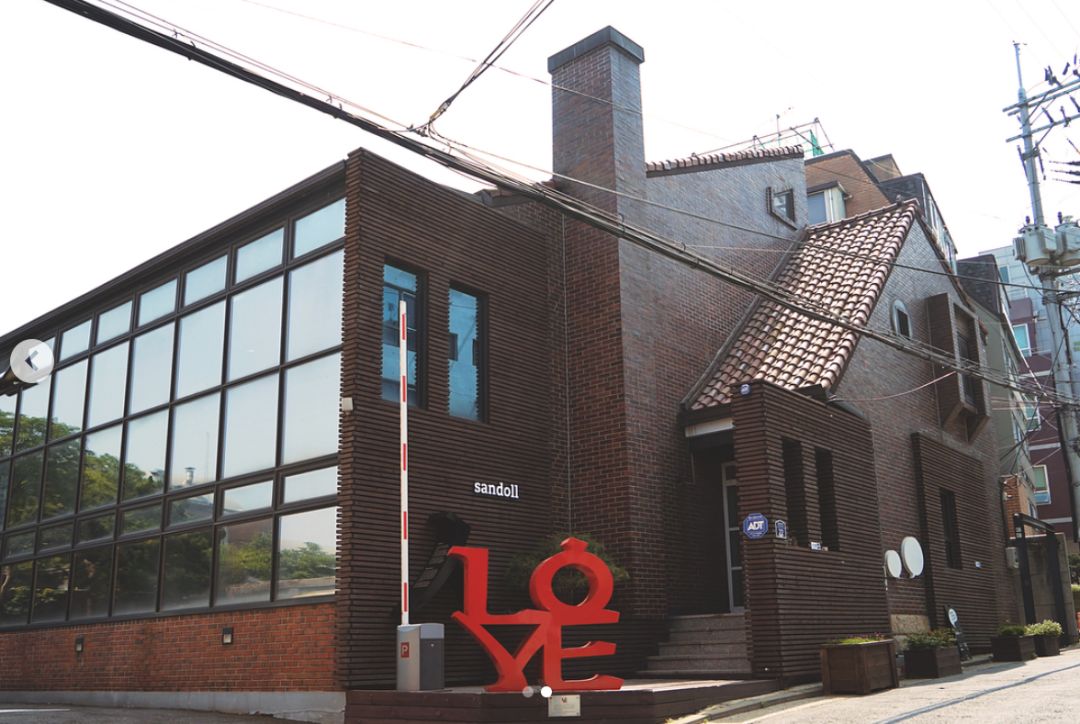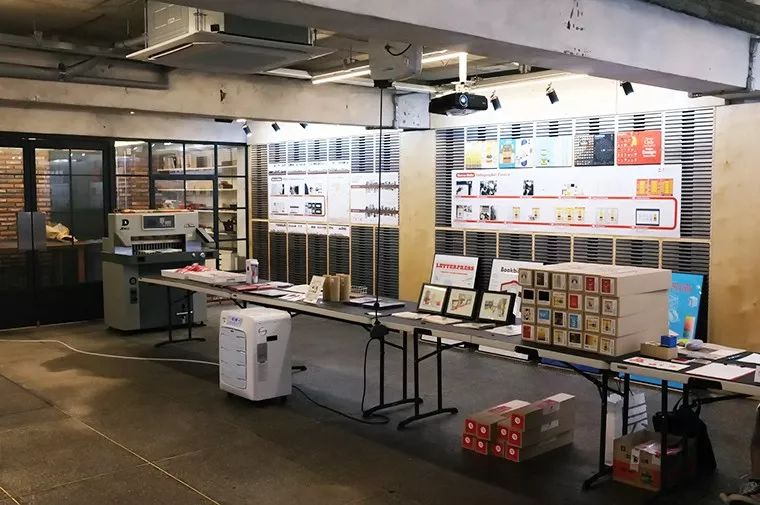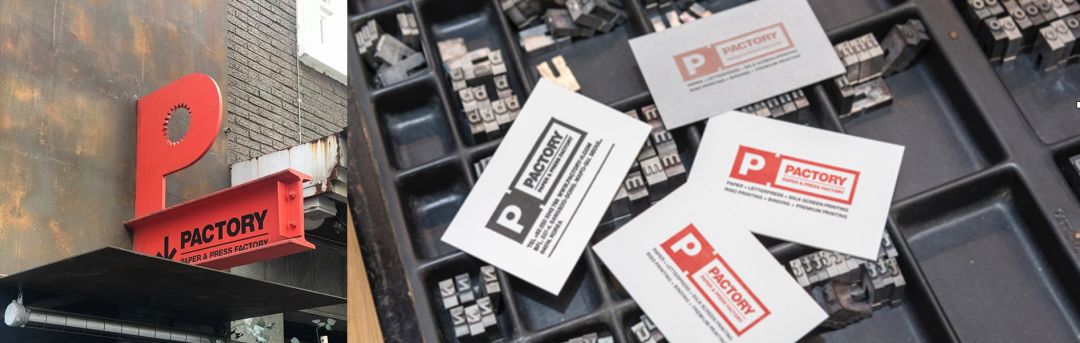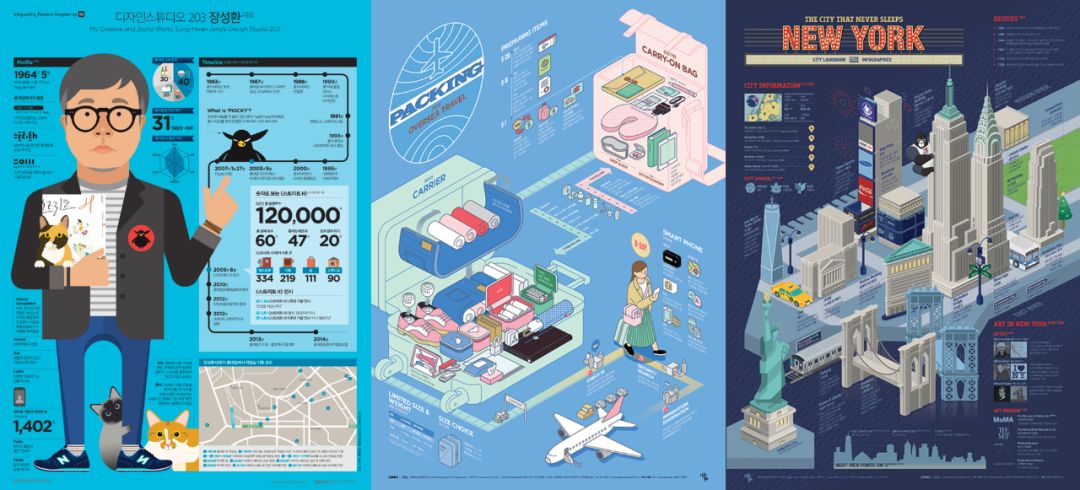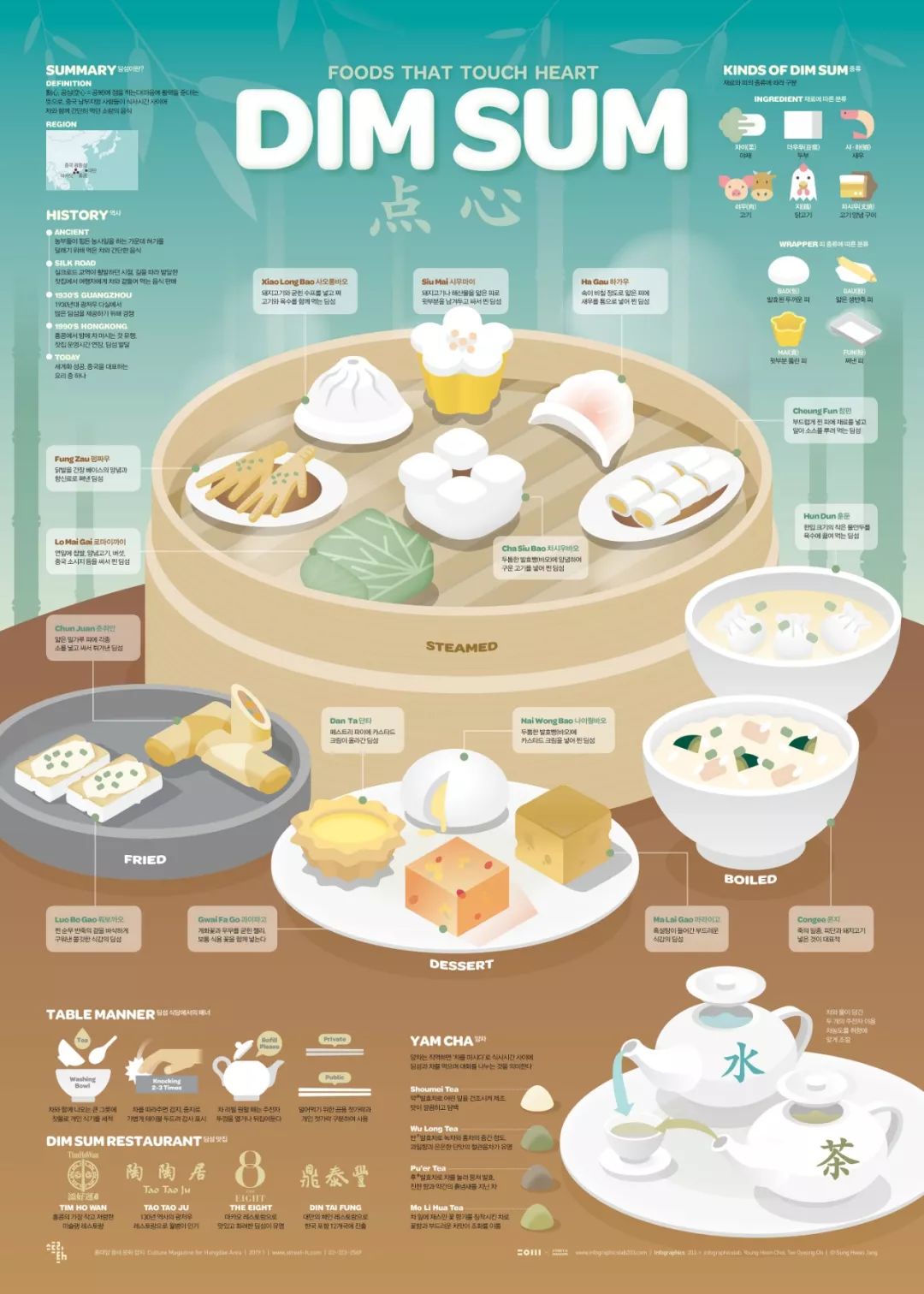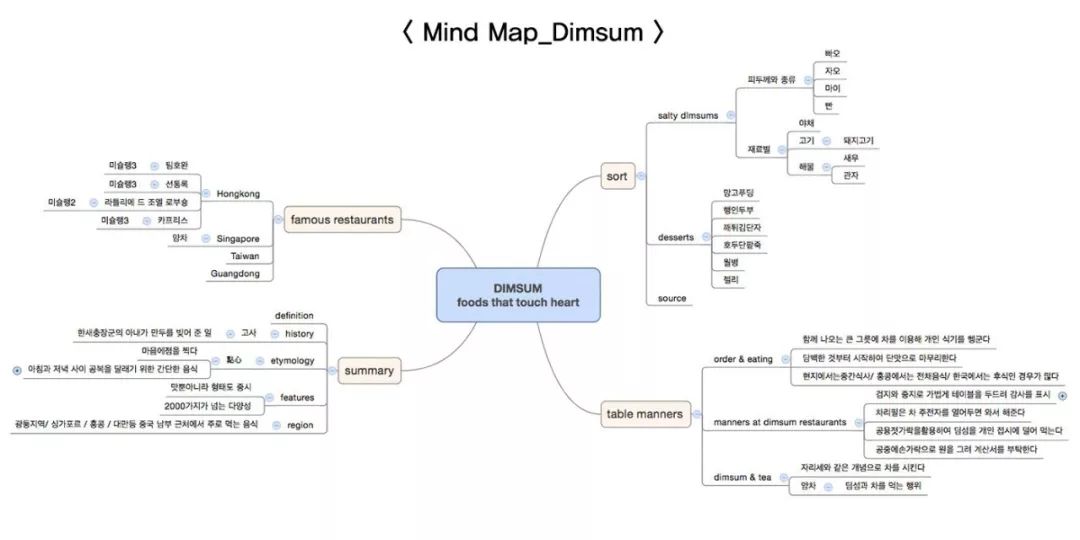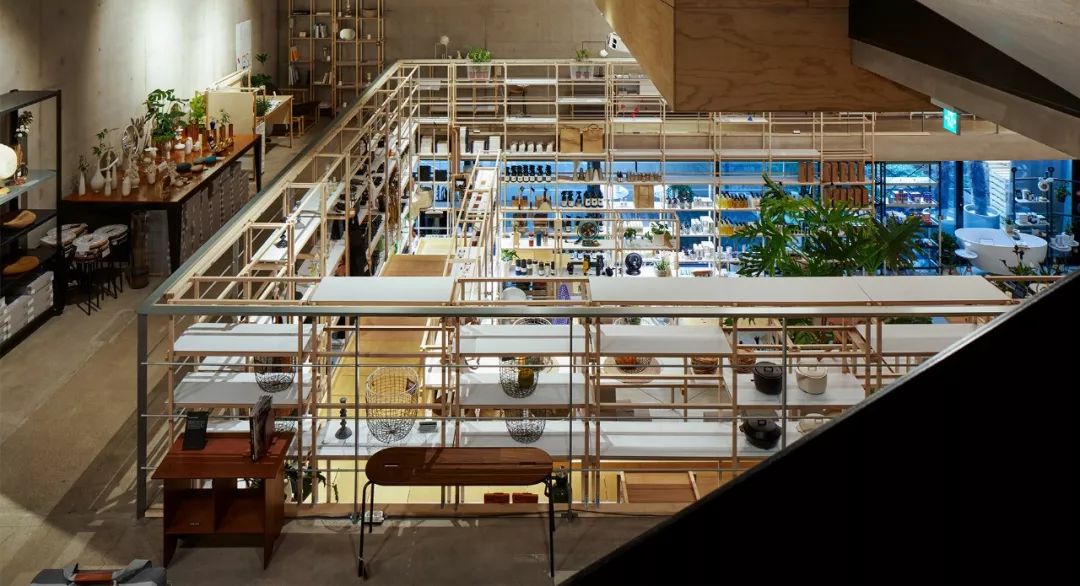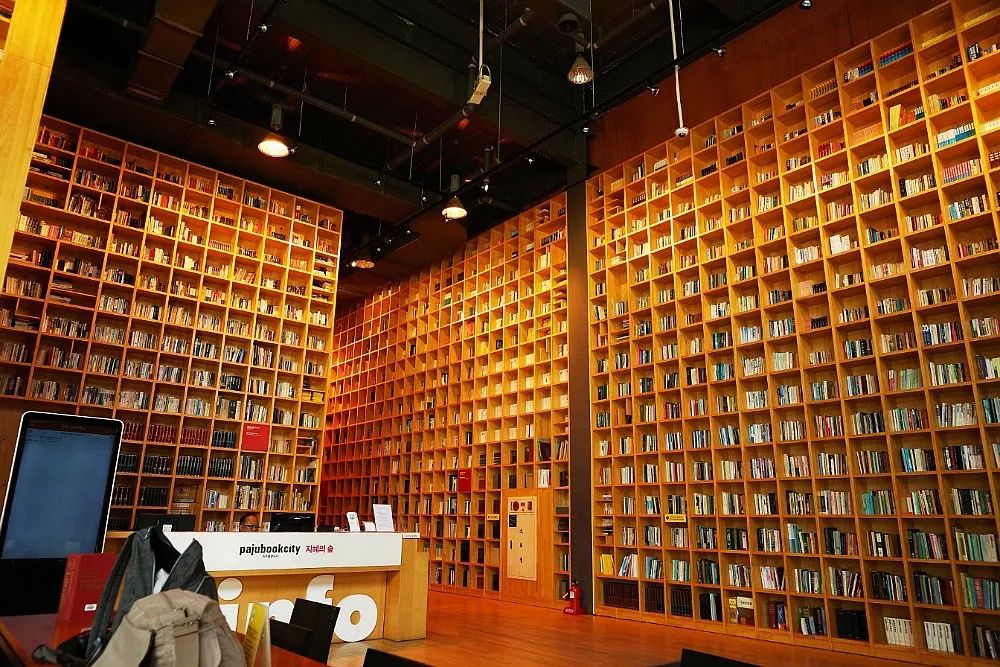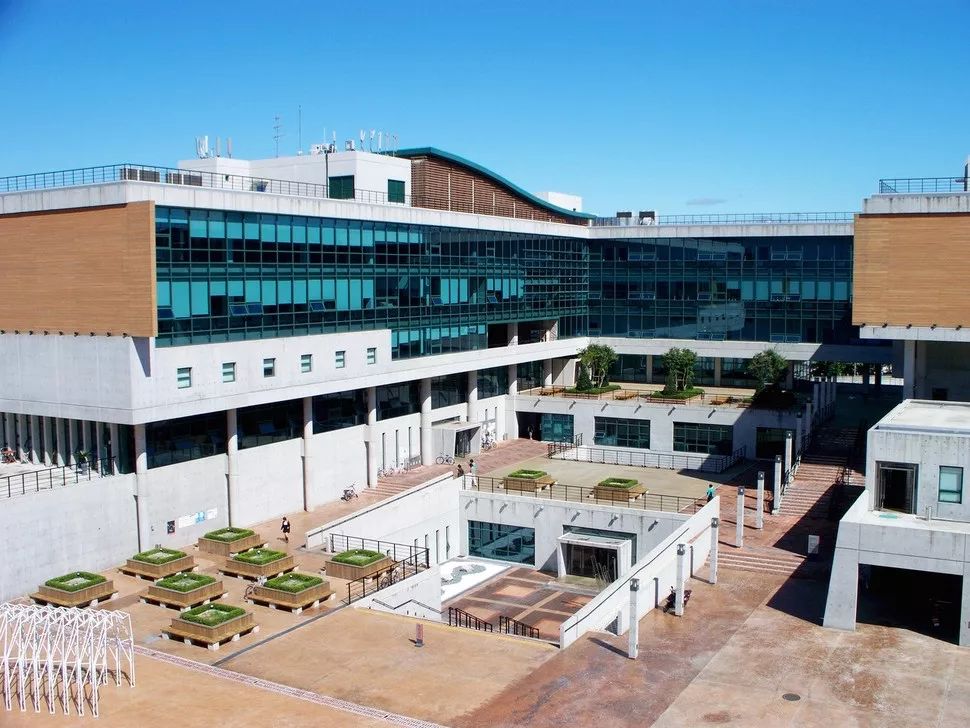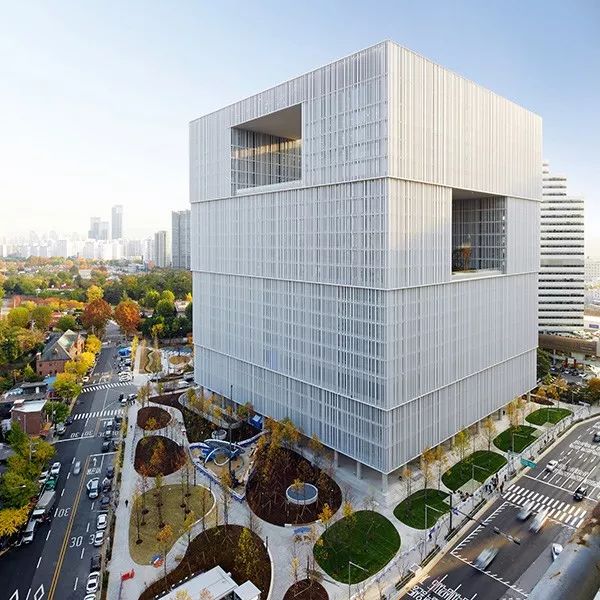
如果五一去韩国,可以拜访这些设计室
上世纪末开始,韩国在国际上呈现出一种彰显动态或者张力的态势,尤其在世纪之交的几年内,韩国成为全球第四个国民经济发展最快的国家。
近几年更引人注目的是,来自韩国的一系列充满时尚气息的设计与文化产品越发引起业界和世人的关注,一时间「韩国设计」成为又一种个性时尚风格的代名词。
韩国著名设计工作室
韩国著名字体公司  Sandoll
“Sandoll 成立于1984年,韩国第一家将其命名为 ”Sandoll typographics“ 的铸造厂。
第一款同时支援中日韩的开源字体,是 Adobe 与 Google 之间通力合作的思源字体系列(都以开源方式并在 Typekit 上提供),旨在解决在东亚地区统一字体的问题。韩文字体设计部分就是由韩国 Sandoll Communication 完成设计。
在位于myeongnyun-dong的一间小单间,Sandoll在没有员工的情况下开始营业。从那以后, 30年来,我们一直在不遗余力地开发近600种字体。现在,Sandoll已经拥有近40名员工,来自其代表性的seok geumho,他拥有超过30年的字体设计经验,刚刚开始他们的职业生涯的新秀设计师。Sandoll已经制作了努力传播hanguel型字体的重要性和美感。
203 x Infographics Lab
203 x Infographics Lab 为张圣焕先⽣创⽴的较早信息设计专⻔⼯作室。也是较早发起信息设计理念的公司之⼀。
Pactory 印刷工坊
设计师的天堂
Pactory 是位于弘益⼤学附近的集纸张和印刷的⼩型⽣产实验⼯⼚。此地曾为⼩塑料⼚,2016 年由纸张专家崔先⽣和信息设计师张先⽣共同创办的印刷⼯坊。⼯坊有 1500 多种内⽂纸,在这⾥还可以体验部分活字印刷,丝⽹印刷,孔板印刷,以及⼿⼯装帧。
Doosung Paper
韩国两大纸业之一
⼿⼯装帧。Doosung Paper 的中⽂为「⽃星纸业」。是韩国两⼤纸业之⼀。 集纸张印刷,展览的复合空间。
设计好地方
景福宫 / ⻄村 / ⾸尔市⽴美术馆
此区域为钟路区,也是传统与现代融合的⾸尔中⼼地区。 钟路区也做为观光胜地,游历首尔不容错过的地⽅。 景福宫是朝鲜半岛历史上最后⼀个统⼀王朝——朝鲜王朝(李⽒朝鲜)的正宫(法宫)。
宫的正⻔为光华⻔,以宫的地域为中⼼北部为北村,西部为西村。 北村留有传统建筑-韩屋,则西村⽬前发展为⽂艺聚集地。
⾸尔市⽴美术馆是由⾸尔市政府开设的,以展⽰国内外代表艺术品为主。 ⾸尔市⽴美术馆位于代表⾸尔的浪漫街道德寿宫⽯墙路上,是在市中⼼的浪漫和闲趣中,能够尽享艺术乐趣的令⼈向往的美术馆。 德寿宫原来是朝鲜成宗(1469−1494)的哥哥⽉⼭⼤君(1454−1488)的住宅。光海君(1575−1641)即位后将其改称为景云宫,从⽽使之具有了王宫的⾯貌。后来⼜改称为德寿宫。⽬前正在展出 David Hockney展。
韩国艺术综合⼤学
韩国艺术综合⼤学为韩国唯⼀⽂化部下属的国⽴艺术综合⼤学。学校共有6⼤院:⾳乐学院,影像院,戏剧院,舞蹈院,美术院,传统艺术院。⽬前与中国的合作院校有:中央美术学院、北京电影学院、上海戏剧学院等中国各⼤艺术学院。 其设计专业属美术院,教师团队也是在各领域的佼佼者。 教授团队中不仅有AGI成员,讲师团队也都是⽬前活跃在韩国一线的新锐设计师。
弘益⼤学 / 望远洞 / 延南洞
弘⼤是位于韩国⾸尔的著名艺术类学校-弘益⼤学的简称,通常指的是弘益⼤学的周围。从弘益⼤学地铁⼝出来,就会感觉到⼀股艺术的暖流吹过,独特的建筑物,⼤⼤⼩⼩,装饰独特的餐馆,咖啡厅,书店,还有各种规模的展览展⽰画廊。弘⼤是⼀个属于年轻⼈的街道。⾛在被称为艺术与⼈⽂相结合的弘⼤艺术区。在这个充满艺术⽓息的地⽅,是现代韩剧的⾸选地。 望远洞与延南洞则临近与弘⼤区。
韩国独⽴出版物、设计书籍最齐全的书店
Parrk books 在 Queenmama Market 的第三层。是⼀个为⼤⼈的书店。位于岛⼭公园的 Queenmama Market ⼀层为绿⾊产品点,2 层为创意店,4 层为咖啡厅。Parrk 书店⾥不仅摆放⻬全韩国独⽴出版物,同时可以看到诸多外⽂优秀图书。从书店看向岛⼭公园,四季景⾊优美引来很多年轻设计师特意洞书店参观。
设计师最热衷的地方:汉南洞
汉南洞也是⽬前在⾸尔⽂艺⻘年时常聚集的地⽅。 不仅有独特建筑的美术馆,也有很多⽂化艺术⽹红店。 其中 Amorepacific 和 Leeum 美术馆做为传统与当代艺术融合美术馆,也是韩国设计师们热衷的地⽅。
坡州书城
历经 20 多年建成的韩国坡州出版城汇集数百家出版社,拥有国际会议中⼼、展览中⼼、流通中⼼、亚洲书籍艺术中⼼、印制纸张企业、书店、设计事务所及活版印刷⼯房,与⾃然相融的每座建筑均有独特的形态和艺术审美追求,这是⼀座世界独⼀⽆⼆的书籍⽂化和阅读胜地,有许多令⼈感动和对⽐学习之处。
韩国著名设计师安尚秀
创办的民间设计学校 PaTI
对于当下韩文的变化,就不得不提安尚秀。他被认为是重现韩文之美的设计师,并且在 1985 年设计创建了「安体」,这种字体突破了汉字正方形的形状,而变化出万般形状。安尚秀是一位世界级的艺术家,他有一张一只手遮住一只眼的照片成为属于他的图示。
PaTI 则是安尚秀⽼师创办的韩国⺠间学校。没有国家扶持,也没有教育扶持,是安⽼师和有理想的设计师们⼀步⼀步建起的设计专⻔学校。其教育体系也是结合包豪斯的教育理念为培养专业、创意型⼈才⽽做努⼒,在 PaTI 或许还能巧遇安老师。